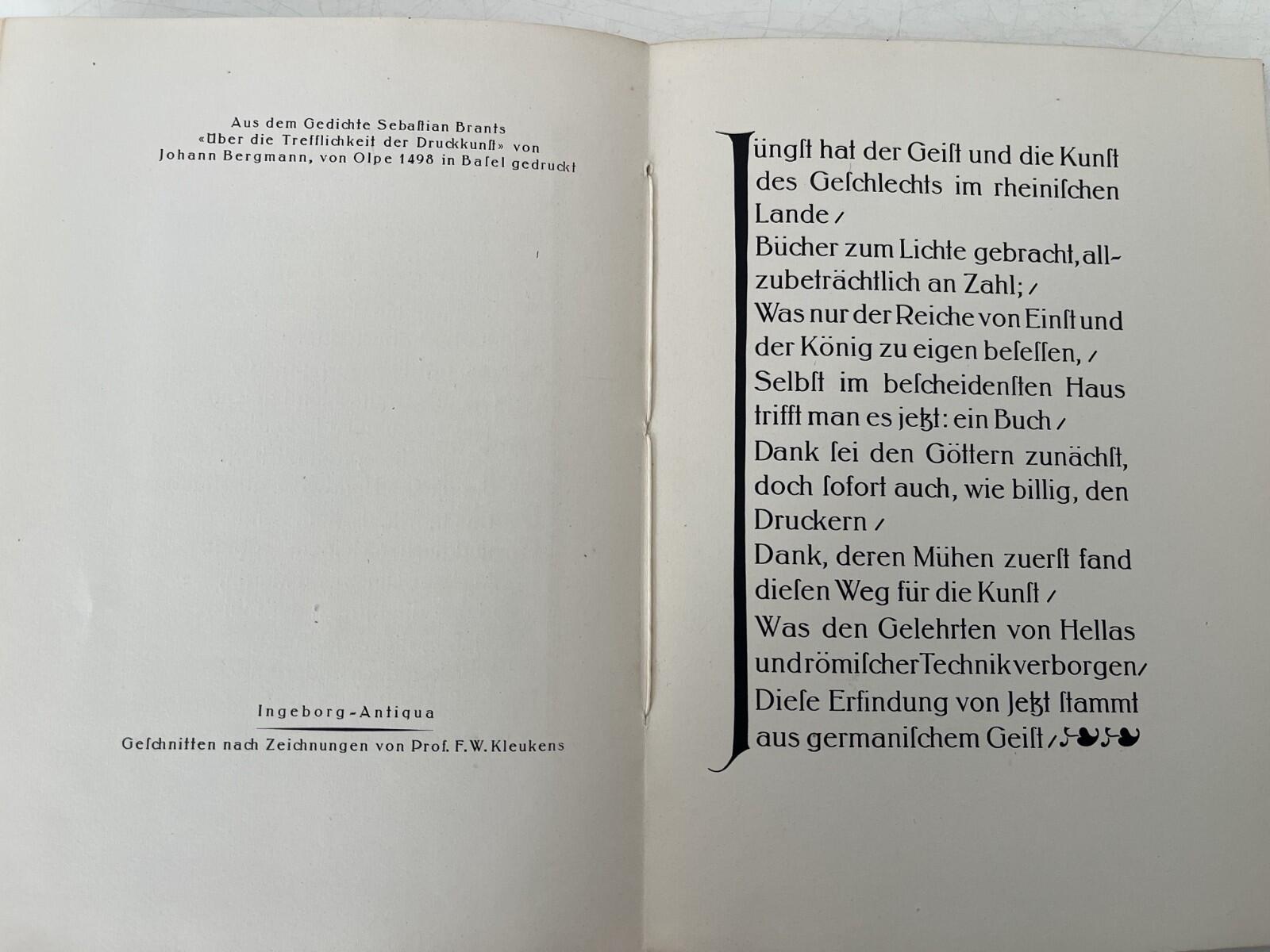
Ingeborg-Antiqua (Kleukens) digitalisieren
als neuer Benutzer habe ich mir einige Beiträge in den Foren bezgl. der Ingeborg-Antiqua angesehen.
Ich arbeite zur Zeit an einer Publikation von 1923 (regionale Geschichte), in der ich diese Schrift verwenden möchte.
Gitbt es hier einen Typo-Designer, der an der Digitalisierung dieser Schrift interessiert ist, bzw. schon Glyphen von dieser Schrift digitalisert hat?
Es wäre schade, wenn ich z. B. auf die Helga-Antiqua ausweichen müsste, da mir der Charakter dieser Schrift am besten für das Thema der Arbeit geeignet erscheint.
(Kühle Strenge und doch elegant)
Es geht mir darum, die Schrift zu verwenden, also diese käuflich zu erwerben. Alle INFOS zu der Schrift, die im Netz verfügbar sind, sind mir schon bekannt. Es geht mir ausschließlich darum, die Schrift zu digitalisieren bzw. diese von einem Anbieter käuflich zu erwerben. Ich kann leider nicht mit einem Programm wie z. B. fontforge umgehen. Ich kann lediglich dabei behilflich sein, die Kurvendateien der Glyphen der Schrift zu erstellen. Mit dem Kerning und weitere Bearbeitungs-Funktionen kenne ich mich zu wenig aus.
Ist auch ein kompliziertes Thema. Ich hoffe, ich finde hier eine Person, die sich damit auskennt und evtl. schon Glyphen der Schrift erstellt hat.
Der Aufwand eine Satzschrift zu digitalisieren ist nicht unerheblich da abgesehen von den Outlines der Glyphen ja noch diverse andere Dinge in den Font einfließen. Bis sich ein ausgewogenes Satzbild ergibt braucht es seine Zeit und ich vermute das sprengt den Rahmen bzw. das Budget.
das ist mir schon bewusst. Ich hoffe halt, das sich hier Leute finden, die schon damit begonnen haben, diverse Glyphen zu digitalisieren. Da ist ja schon das Problem, alle geschnitten Zeichen in einer ordentlichen Große zu finden um sie scannen zu können. In Schriftmusterbüchern sind auch nicht immer alle Zeichen vorhanden. Ich muss halt warten …
das ist die bisher beste Alternativ-Schrift zu der Ingeborg-Antiqua. Werds mir überlegen.
danke für die Info zur Orient-Antiqua. Ich habe die Ingeborg-Antiqua zu größeren Teilen digitalisert.
Mir fehlen noch ein paar Zeichen. Ich weiß nicht, an ein Alphabet zu kommen, das groß genug zum Abkupfern ist.
Falls du in Deinen Beständen z. B. die Ligaturen hättest und mir zur Verfügung stellen würdest, ware das toll.
Die Zeichen ( ) ! § ? & % habe ich mir schon herstellen können. Die Vorlagen waren zwar mäßig, aber das Ergebnis ist sicher vertretbar.
Das Muster hat rund 40 Seiten und mindestens die Hälfte davon zeigen wahrscheinlich die Ingeborg-Antiqua. Im besten Fall fehlen die zwei Seiten bei der Kleukens Fraktur … wenn nicht bleiben immer noch 18 Seiten.
Hier ist die oben bereits gezeigte Seite nochmal aus einer anderen Quelle.
Hier wird die Ingeborg nochmal in verschiedenen Schnitten und Anwendungen behandelt.
vielen Dank für die Infos. Mitlerweile habe ich ein ordentlich gescantes Alphabet gefunden.
Die Alphabetsammlung zu Skizzierzwecken der mageren Version ist jetzt bei der DNB frei zugänglich.
Das (genauer: das) müsste es sein. Ich glaube, man kann oder konnte dort auch gegen Geld höhere Auflösungen anfragen.
Ja, bei mir auch. Ich habe dann über den Scan und Kopierservice dort ein Formular ausgefüllt, um die Digitalen Daten zu erhalten.
Dann kam eine Antwort: Das Medium wäre nun freigeschaltet. Sofort ausprobiert und "nur im Lesesaal möglich" war verschwunden.
Ich glaube aber nicht, das das automatisch so geht ... Bei anderen Medien wirds wohl nicht immer so problemlos funktionieren.
Jetzt fehlt mir das schöne Muster für die Halbfette und Kursiv-Variante.
Was da jemand, wo man die findet? Hat die Stempel AG die Skizzenbücher evtl. in süpäteren Jahren herausgegeben?
Die Kursiv und Halbfett ist ja auch später geschnitten worden.
Ich bin “a day late and a dollar short” wie wir hierzulande sagen. Das einzige Beispiel das ich habe besteht nur aus Buchstaben und Ziffern, und damit bist Du ja schon gut versehen.